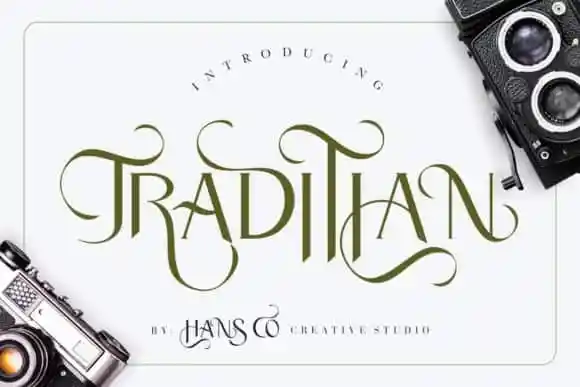
Traditian Display Font – Fonte Grátis
Traditian Display Font
Traditian Display Font é uma elegante e única fonte moderna que traz estilo próprio para qualquer projeto de design. Inspirada na tipografia clássica, essa fonte exótica e luxuosa oferece muitas opções de ligação e alternativas para criar ambientes impressionantes em sua apresentação. É perfeita tanto para headlines quanto para blocos de texto que possuem variações extremas e minimais, seja para sites, impressão ou vídeos em movimento. Seja qual seja o formato do seu projeto, Traditian irá brilhar sob qualquer luz.